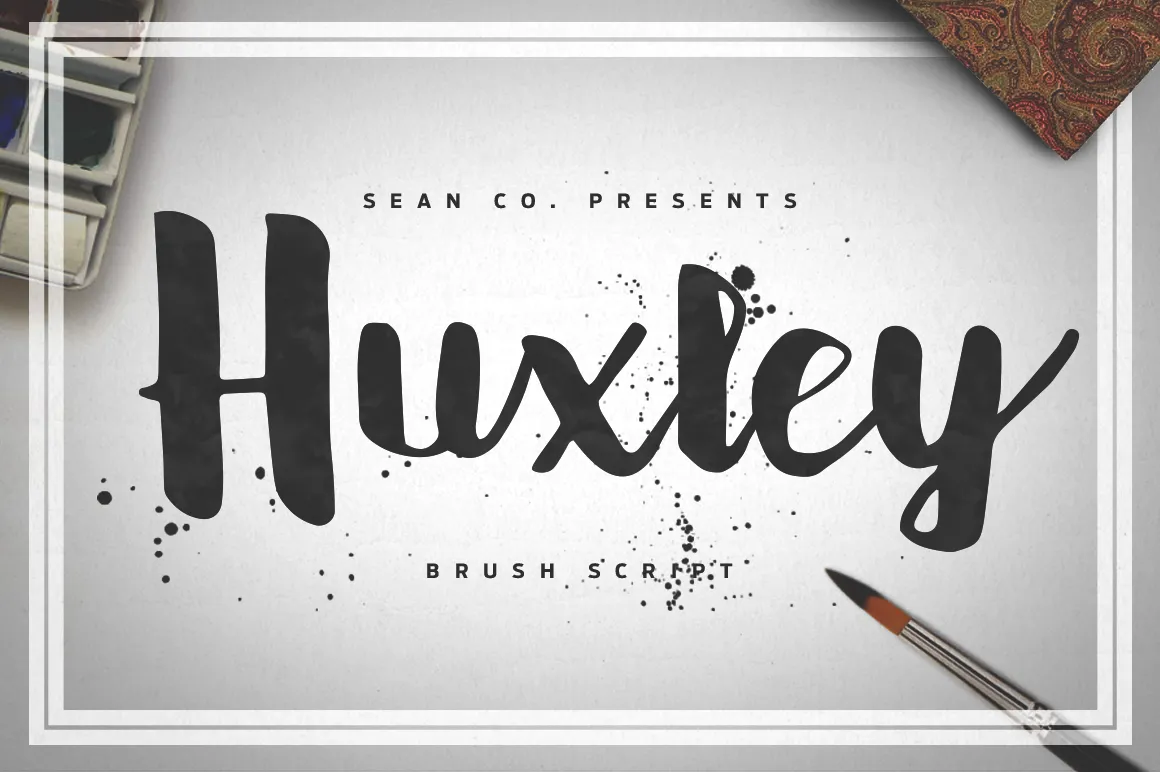
A nova HuxleyScript Font é uma escolha perfeita para quem busca uma tipografia delicada e elegante que se destaca em qualquer projeto. Introduzida especialmente por Hamilton, essa fonte Script foi criada com designers e especialistas em design gráfico em mente. Ela oferece um toque refinado que complementa bem designs como camisetas, folders, mug designs e até mesmo postais. Uma das características notáveis é a sua versatilidade; ela inclui alternativas maiúsculas e minúsculas, além de seleções de swashes que dão mais flexibilidade aos seus projetos. Além disso, oferece suporte multilinguístico para facilitar o uso internacional. Se você busca uma fonte Script poderosa e versátil, a HuxleyScript é definitivamente algo que vale a pena considerar em sua próxima criação visual.